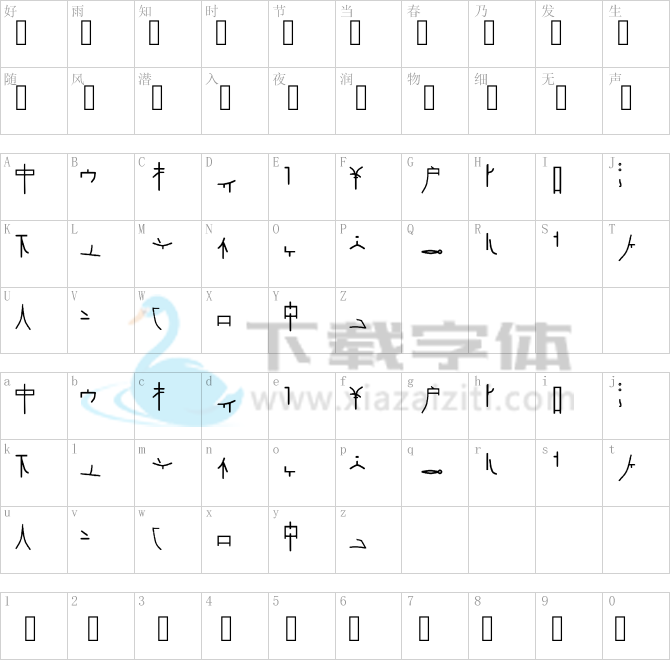
Alphacode Emperor.ttf字体下载
Alphacode Emperor.ttf字体下载,这款字体结构工整、笔画清晰,兼顾美观与易读性,适用于标题、正文、海报、包装、LOGO 等多种场景。字形优雅稳定,风格百搭耐看,适配日常排版与创意设计,让文字呈现更舒适、更具质感。Alphacode Emperor.ttf字体下载一笔一画,皆是细节,以均衡的比例、流畅的线条打造舒适视觉体验,字形端正大气,风格简约现代。无论是商业设计、品牌宣传还是日常排版,都能轻松驾驭,让文字更有格调与力量。Alphacode Emperor.ttf字体下载字体下载。